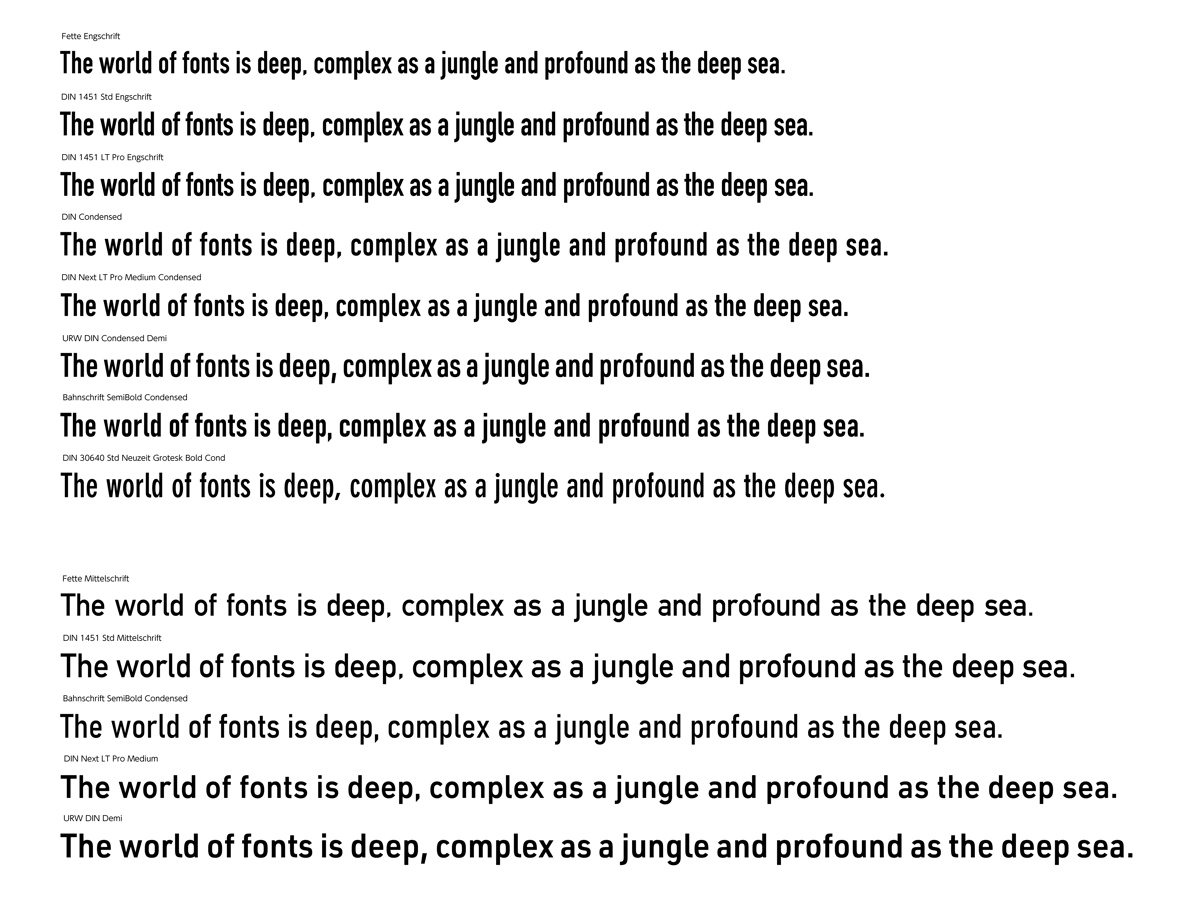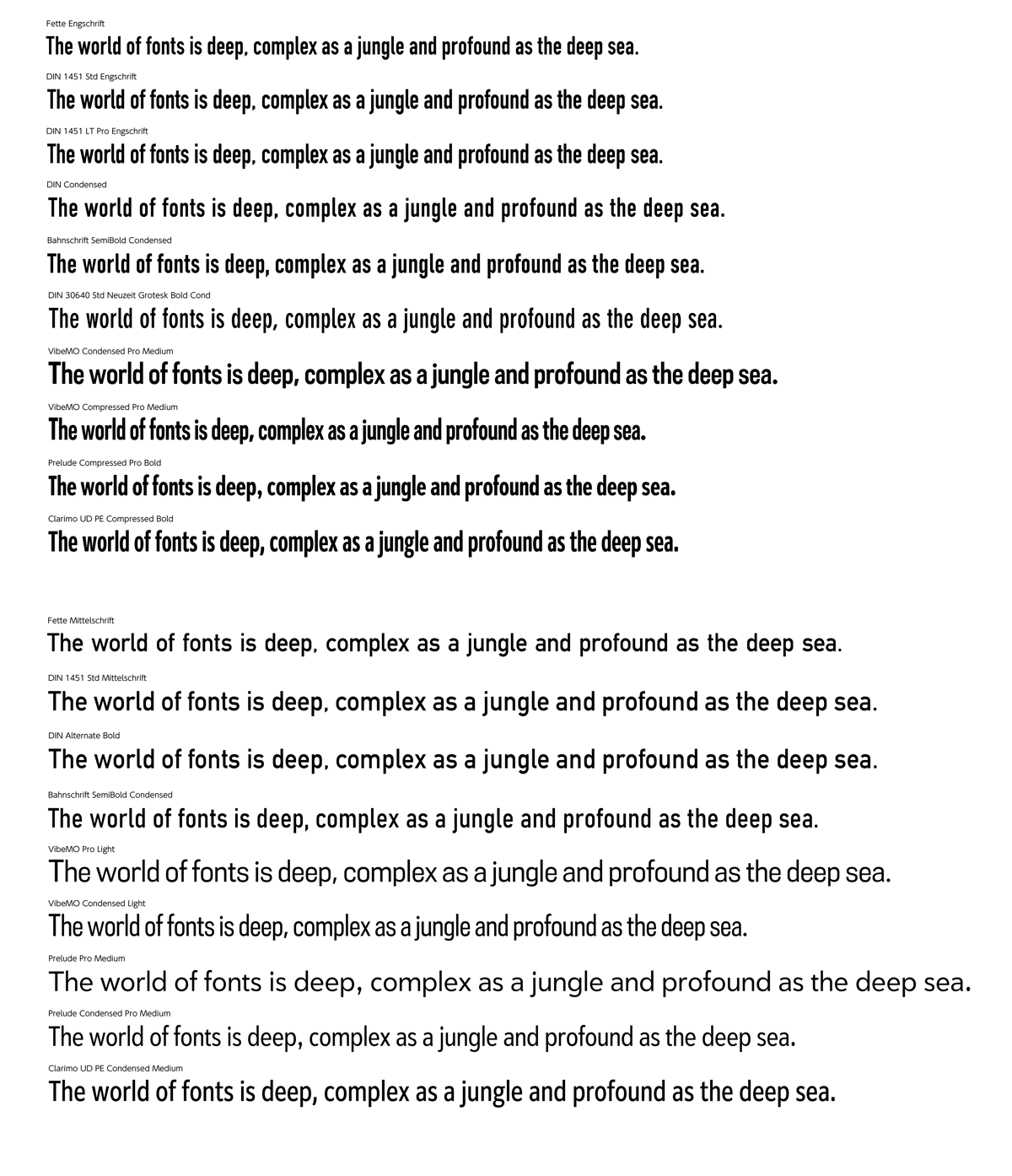
Fette Engschrift, Fette Mittelschrift と似たフォントを利用したい
Fette Engschrift, Fette Mittelschrift と似たフォントを利用したい場合のフォントを紹介します。
類似フォント
Fette EngschriftやFette Mittelschriftと似たフォントを使用したいが、Fette Engschrift Regular、Fette Mittelschrift Regular のフォントが無い場合は、 "DIN 1451" "Bahnschrift" "DIN Alternative" が類似のフォントとして利用できます。
また、"DIN Next", "URW DIN"も代替として利用できます。
別名
"Fette Engschrift"と同一の書体を "DIN"と呼んでいる場合もあります。この場合は、"DIN" を使用すると,Fette Engschriftとほぼ同一の書体になります。
書体比較
各書体で文字幅や太さが異なるため、印象が若干違いますが、イメージはおおむね一致しています。
横幅は"Fette Engschrift"が一番短いため、詰まっている感を出したい場合には、DINフォントを利用する場合は、文字間を調整するなど若干工夫が必要そうです。
その他の代替フォント
細かい形状が異なりますが、Fette Engschriftと雰囲気が似ているフォントとしては、若干線が太いですが、VibeMO Compressed が挙げられます。
Prelude Compressed, Clarimo UD Compressed もやや似ていますが、Fette Engschriftと比べると、やや丸みがある印象です。
"O"の文字がやや四角形に見えるフォントのほうが雰囲気が似ます。
Fette Mittelschriftに似ているフォントでは、Clarimo UD Condensedが似た印象になります。VibeMO は線がやや細く鋭角感が強く、 VibeMO Condensedではやや詰まりすぎの印象です。